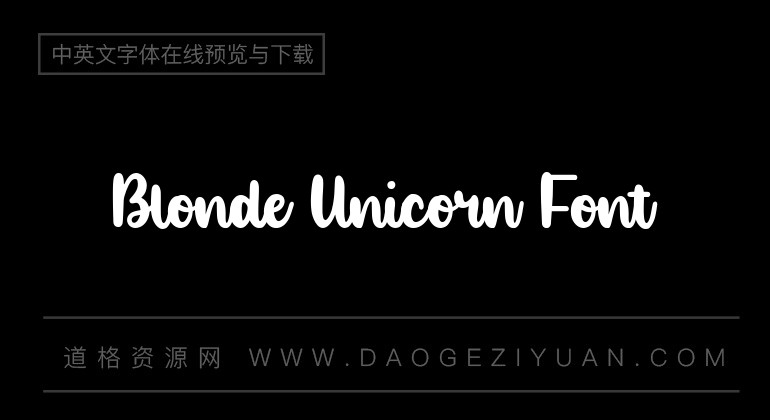
Blonde Unicorn Font 是一种华丽的手写字体。它具有流畅的笔画和优美的弧线,字母形状独特,既有现代感又有一定的复古风格。 这种字体的特点是每个字母都有一些装饰性的元素,例如弯曲的线条、花纹和点缀。这些元素为文本添加了一些额外的视觉吸引力,使其在各种设计项目中都能脱颖而出。 Blonde Unicorn Font 适用于各种设计项目,包括印刷品、海报、名片、包装设计等。由于其华丽的外观和易于阅读的特点,它也是婚礼和派对邀请函的理想选择。 该字体提供了多种格式,包括TrueType和OpenType,可供Windows和Mac用户使用。内容介绍
Blonde Unicorn Font是一款非常不错的手写艺术字体,具有很好的视觉感,适合于文化类的宣传设计、商业类品牌的广告和产品包装设计以及个性化文字排版等较多场景。